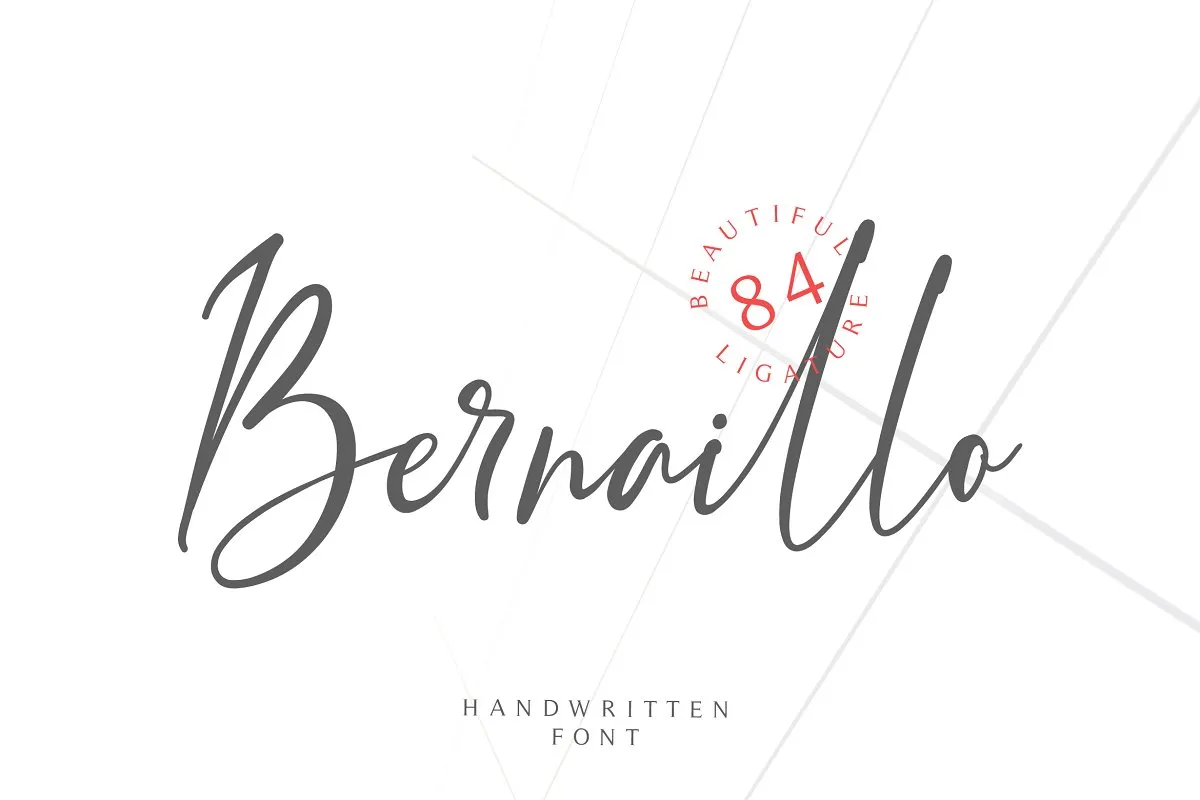
Estou aqui uma fonte que se destaca entre as demais, Bernaillo Script Font. Desenvolvida pela designer Pen Culture e compartilhada pelo designer 0001themes, essa fonte é um must para aqueles que procuram diversidade e versatilidade em suas criações digitais. O Bernaillo Script oferece uma grande variedade de usos possíveis, tanto para projetos grandes quanto menores. Com seus suportes inclusivos a letras maiúsculas e minúsculas, números e pontuação, além das incrivelmente belas ligaturas de 84 opções, o Bernaillo Script é uma escolha ótima para criar identidades digitais fortes. Suas capacidades multifuncionais tornam-na perfeita para uso em aplicativos como logotipos de marca, selos digitais, cartões de negócio e nomes empresariais. É uma fonte que se destaca na categoria de Script Fonts, com um design único e extremamente atraente. Suas ligaturas multifuncionais são realmente úteis para criar uma identidade visual única e personalizada. A Bernaillo Script Font é certamente um investimento valioso para qualquer designer ou criativo que busca qualidade, versatilidade e estilo em suas fontes digitais.